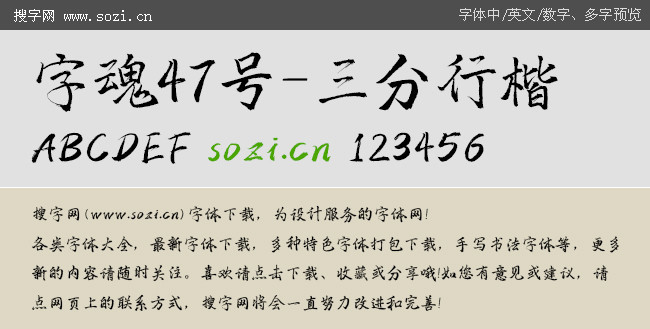
字魂47號(hào)-三分行楷
搜字網(wǎng)提供一款字魂47號(hào)-三分行楷中文字體下載,該字體是一款毛筆書法手寫字體,該字體包含6763個(gè)中文、字母、 符號(hào)和數(shù)字,具有溫柔、婉約、手寫風(fēng)、簡(jiǎn)約 的風(fēng)格,可以滿足您設(shè)計(jì)上的各種需求,該字體主要用于海報(bào)企宣、書籍、店鋪、活動(dòng)、健康養(yǎng)生 等場(chǎng)景。